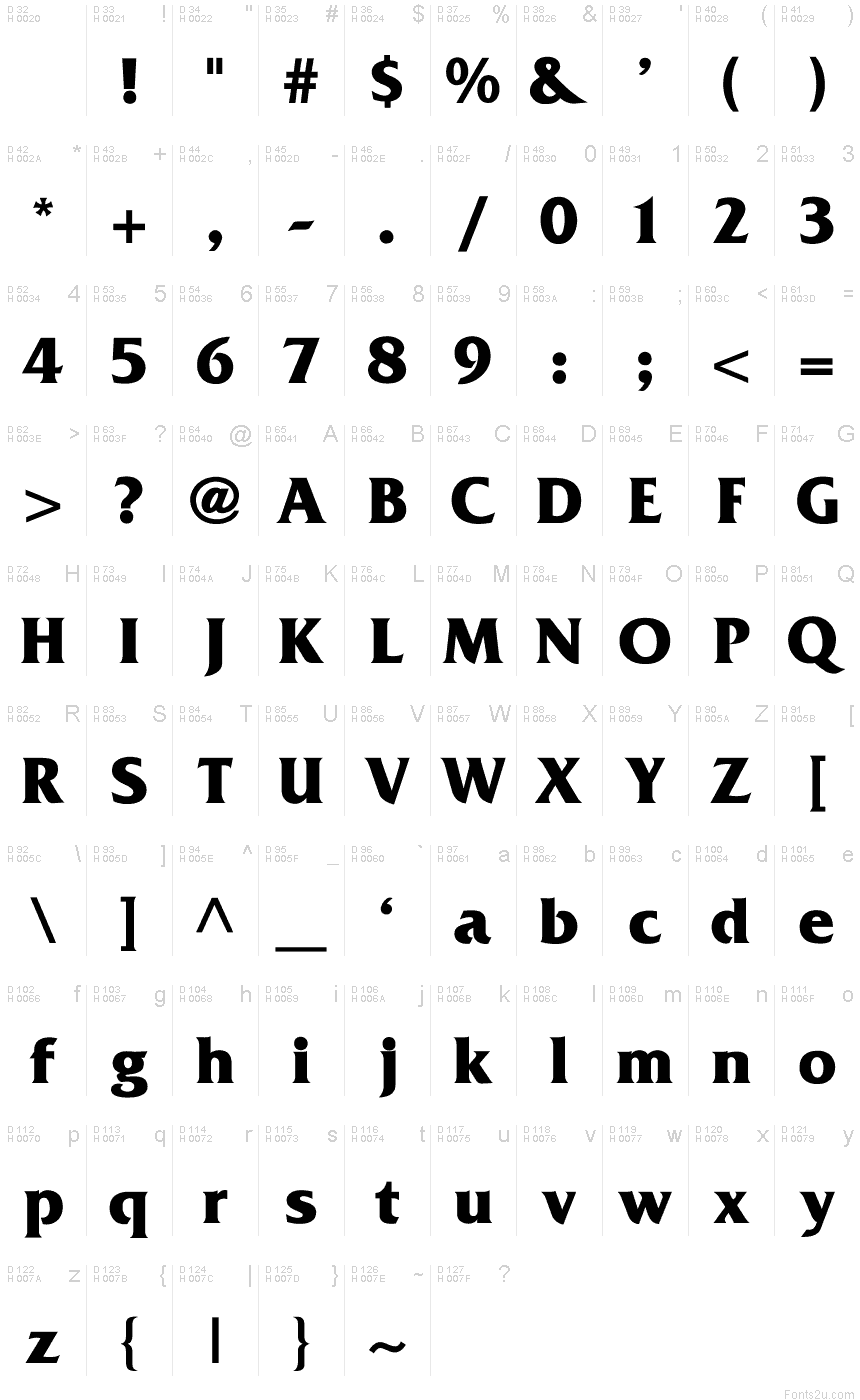
Lyon Bold od Publisher's Paradise to darmowy krój szeryfowy o wyrazistym, głębokim charakterze, który przykuwa wzrok od pierwszego spojrzenia. Jego szerokie kształty, ciasne krzywe i ostro cięte szeryfy przypominają nagłówki starych gazet, ale w bardziej zdecydowanym wydaniu, co nadaje tekstowi solidną, pewną wagę. Rytm między literami pozostaje zwarty i czytelny, dzięki czemu duże słowa układają się w wyrazisty, mocny blok.
Lyon Bold idealnie sprawdzi się na okładkach książek, w nagłówkach redakcyjnych, na plakatach, opakowaniach oraz w oznakowaniach muzealnych, nadając im tradycyjny, lecz pełen energii głos. Ten darmowy font najlepiej prezentuje się w większych rozmiarach, gdzie jego gęste formy i ostre krawędzie są doskonale widoczne, podczas gdy mniejsze teksty uzupełniające świetnie komponują się z prostym krojem bezszeryfowym.